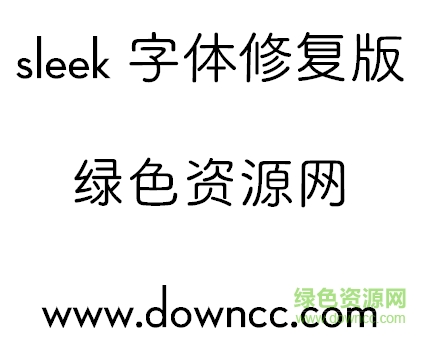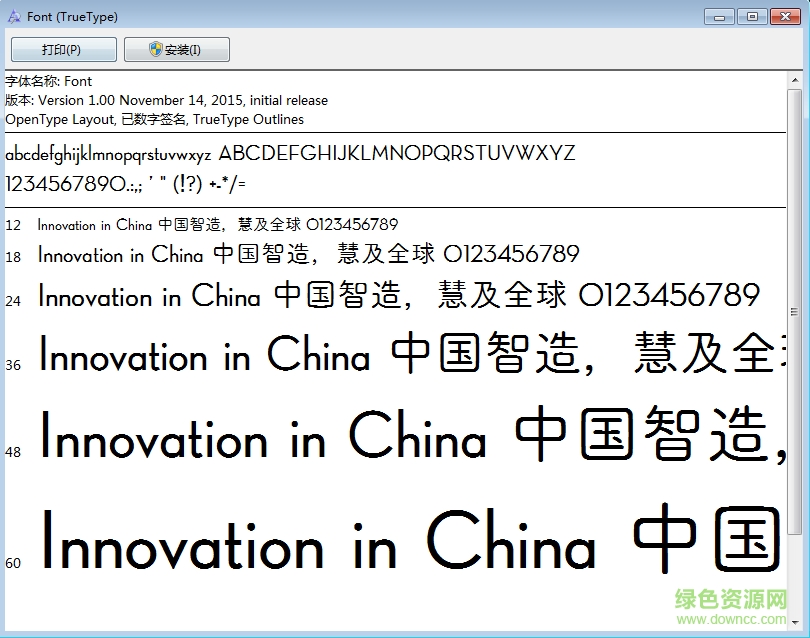
sleek字體是一款字庫較全的古今特色結(jié)合的藝術(shù)字體,獨(dú)特的造型和流暢的字跡讓你的文字閱讀更顯舒適,綠色資源網(wǎng)為大家?guī)矸焙?jiǎn)合集的修復(fù)版本,歡迎下載喲!
sleek , 名字有點(diǎn)怪但字體卻很帥。超時(shí)代的二次元配搭古典且字形整齊方正的漢字吸引了無數(shù)的目光找呀找的,總希望能有個(gè)特符和字庫較全的。今天有了,而且還是簡(jiǎn)繁體合集,接近五萬二千字符的增強(qiáng)版。
1.補(bǔ)全了各種表情,圖片,商標(biāo),各類特符,象形文字,包括中日韓的各種語言文字音符,各領(lǐng)域?qū)S梅?hào),字母數(shù)字等等 24,340 個(gè)。
2.字體包含了 27,492 個(gè)漢字(簡(jiǎn)+繁+生僻字)
3.修復(fù)了稍微上移的中文字,因功力尚淺也沒把尺在手所以沒能調(diào)至100%的準(zhǔn)確(強(qiáng)迫癥的門外看看就好了哈)
4.小寫字母沒有加大卻優(yōu)化了平滑(因?yàn)閟leek 也是取意 '平滑'的意思)。
5.修復(fù)了英文標(biāo)點(diǎn)符號(hào)的超級(jí)字距,現(xiàn)在看起來順眼多了。